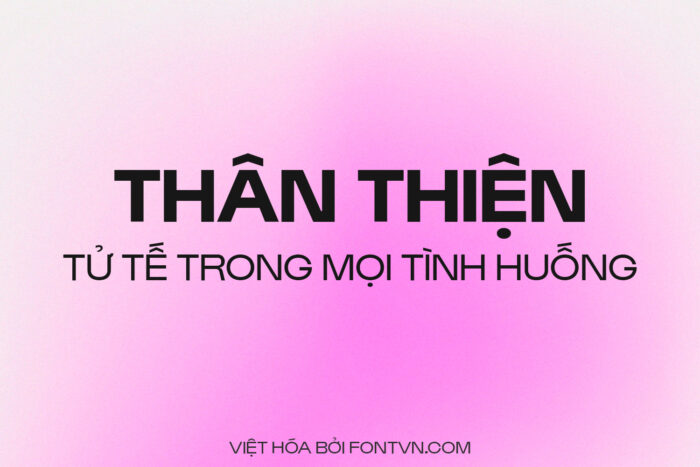
DVN Gustavo Việt hóa – Font chữ hiện đại và mới lạ
Font chữ Gustavo Việt hóa là sự kết hợp tinh tế giữa phong cách hiện đại và cổ điển, mang đến một diện mạo độc đáo và ấn tượng. Gustavo nổi bật với các đường nét thanh mảnh, góc cạnh mềm mại và độ dày vừa phải, tạo cảm giác dễ đọc và thoải mái cho người nhìn. Hình dạng chữ của Gustavo được thiết kế tỉ mỉ, từng chi tiết nhỏ đều được chăm chút để đảm bảo tính thẩm mỹ cao và sự cân đối hoàn hảo.
Gustavo thích hợp cho nhiều ứng dụng khác nhau, từ thiết kế đồ họa, logo, bìa sách, đến các ấn phẩm quảng cáo và truyền thông. Với sự linh hoạt và phong cách đa dạng, font chữ này có thể làm nổi bật các dự án sáng tạo, mang đến vẻ đẹp thanh lịch và hiện đại. Gustavo Việt hóa không chỉ là một lựa chọn tuyệt vời cho các nhà thiết kế, mà còn là công cụ hữu ích cho bất kỳ ai muốn nâng cao chất lượng thẩm mỹ của các sản phẩm văn bản.
Font được Việt hóa 3 Style: Bold, Regular và Medium